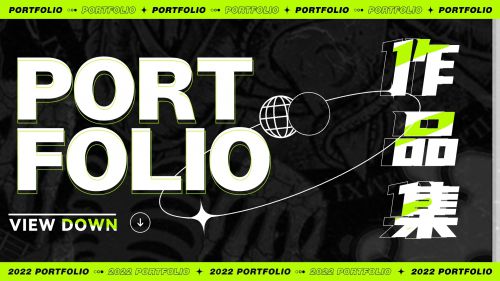
优设标题黑
### 优设标题黑:免费商用的力量感创意字体 优设标题黑是优设字库旗下一款极具现代张力的创意字体,由字由X优设联合发布,支持简体中文常规字符集,且提供免费商用授权,为设计师带来高效实用的视觉表达工具。 优设标题黑以“力量”与“现代”为核心风格,整体字形方正稳健,重心居中的设计让字体视觉平衡感十足,中宫适中的结构既保证了文字的紧凑性,又避免了拥挤感,阅读体验清晰舒适。 在笔型设计上,优设标题黑极具辨识度:笔画多采用利落直角,线条硬朗有力,搭配方头收尾与断开连接的细节处理,既保留了黑体的庄重感,又通过几何化的笔触增强了现代科技感。字重“粗”且粗细均匀的特性,让字体在标题场景中极具冲击力,轻松抓住视觉焦点。 无论是品牌主视觉、广告标题还是新媒体海报,优设标题黑都能凭借其独特的力量感与现代美学,为设计作品注入鲜明个性,是免费商用领域中兼具实用性与设计感的优质选择。